Você gostaria de aprender a transmitir temas complexos de uma forma visualmente atraente e compreensível? Neste curso online, o designer interdisciplinar e artista digital Martin Naumann mostrará a você como criar designs de tipos baseados em grade e animá-los usando métodos baseados em procedimentos e aleatórios.
O trabalho de Martin é caracterizado por cores vibrantes e uma estética futurista, e ao longo de sua carreira colaborou em projetos premiados com clientes como DIE ZEIT e Laroché Chocolate, além de Universal Music e Anjunabeats. Embarque em uma jornada emocionante com ele, deixe-se seduzir pelo acaso e crie animações gráficas impressionantes.
No início do curso você conhecerá o designer interdisciplinar e artista digital Martin Naumann. Ele fala sobre sua trajetória profissional e compartilha com você suas principais fontes de inspiração.
Martin então lhe dará uma visão geral dos fundamentos e terminologias das áreas de design de tipos e arte generativa. Então você se familiariza com a teoria das cores e cria um mood board com a inspiração para o seu tipo de design, escolhendo uma palavra ou uma letra como motivo básico.
Seu professor mostrará a você como desenhar os vetores de suas letras no Adobe Illustrator e exportá-los para depois colá-los no After Effects. Na próxima etapa, você aprenderá sobre alguns efeitos de distorção procedural e gradientes no After Effects e como aplicá-los às suas letras.
Depois disso, você aprenderá a gerar e animar texturas de cores aleatórias para dar às suas letras uma estética viva. Por fim, Martin mostra como exportar as animações individuais como um vídeo ou uma série de imagens generativas e juntá-las em um layout.
Por fim, seu professor mostrará alguns plug-ins para o After Effects e o programa Filter Forge, que você pode usar para realizar projetos semelhantes.
Neste curso você criará desenhos abstratos e montará um portfólio de efeitos que poderão ser usados de forma modular, escolhendo uma palavra ou uma letra como motivo básico.
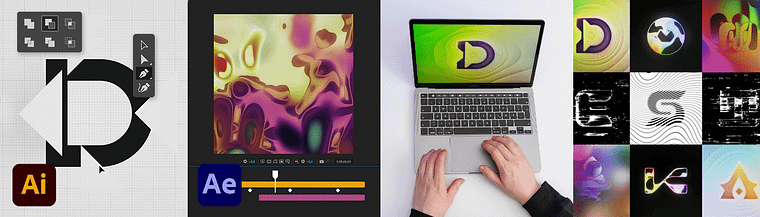
Este curso é destinado a qualquer pessoa interessada em design experimental de tipos, animação ou arte abstrata digital e gostaria de abordar essas disciplinas. Também é adequado para qualquer pessoa que trabalhe nas áreas de design, movimento e design de tipos.
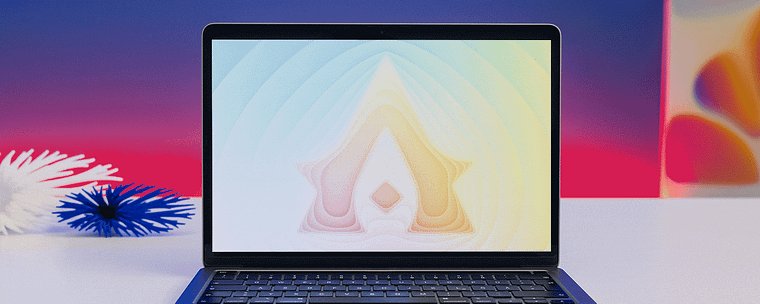
O curso é voltado para designers, artistas e criativos com conhecimentos básicos em design digital que querem explorar novas possibilidades em arte generativa, tipografia abstrata e Creative Coding.
Você vai aprender a criar arte generativa, tipografia abstrata, visuais animados e fontes experimentais usando After Effects, Houdini e Processing — desde o moodboard até a exportação. O foco é em técnicas inovadoras e fluxos criativos.
Sim, depois do curso você estará apto a criar capas digitais personalizadas para álbuns, tipografia animada e visuais impactantes para redes sociais com métodos generativos e experimentais.
No curso, você vai conhecer anatomia da letra, design tipográfico artístico e experimental, identificação de fontes serifadas, otimização da legibilidade e criação de fontes display exclusivas, além de desafios tipográficos.